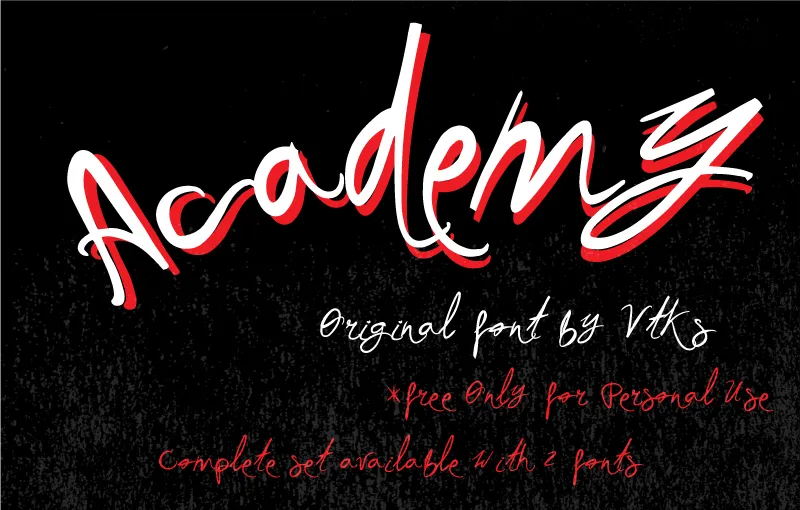
Vtks Academy Font – Download Grátis
A Vtks Academy Font é uma fonte escrita à mão criada por Hamilton, perfeita para quem busca um toque elegante e autêntico em seus projetos digitais. Com linhas delicadas e traços suaves, esta fonte oferece um charme natural e personalizado, tornando-a ideal tanto para aplicativos de design pessoal quanto para criações comerciais. Se você está procurando uma fonte à mão que exibe seu estilo único em projetos digitais, a Vtks Academy Font é sua escolha perfeita. Com versatilidade para uso em variados tamanhos e formatos, esta fonte não apenas adiciona um toque autêntico aos seus materiais gráficos, mas também permite que você expressa seu próprio estilo criativo. Para aqueles desejando adquirir a licença desta maravilhosa fonte à mão, Hamilton disponibilizou uma opção em dólares. Você pode comprar sua autorização de uso através deste link específico. Compre agora e divirta-se com as possibilidades criativas que esta fonte tem para oferecer!